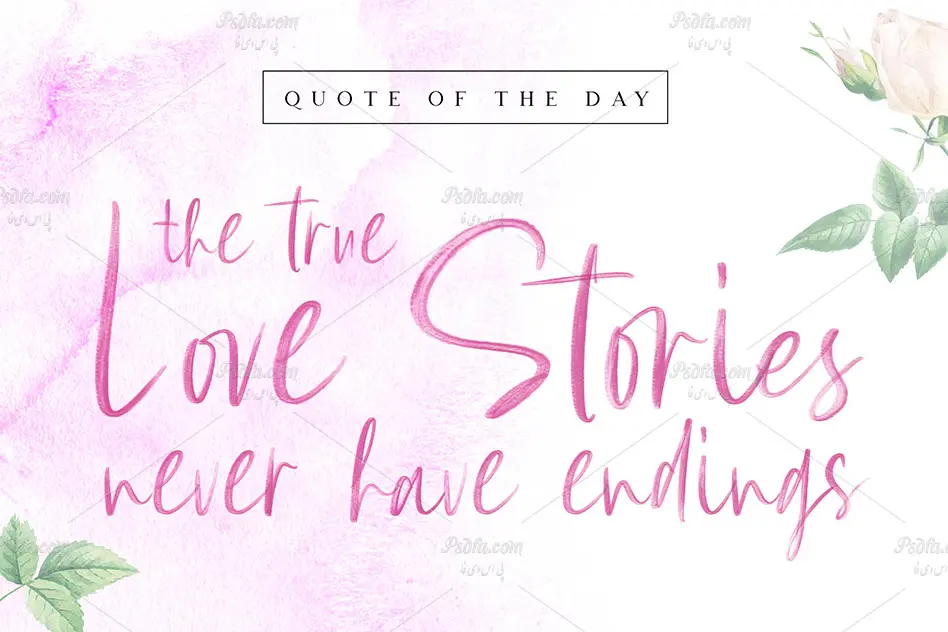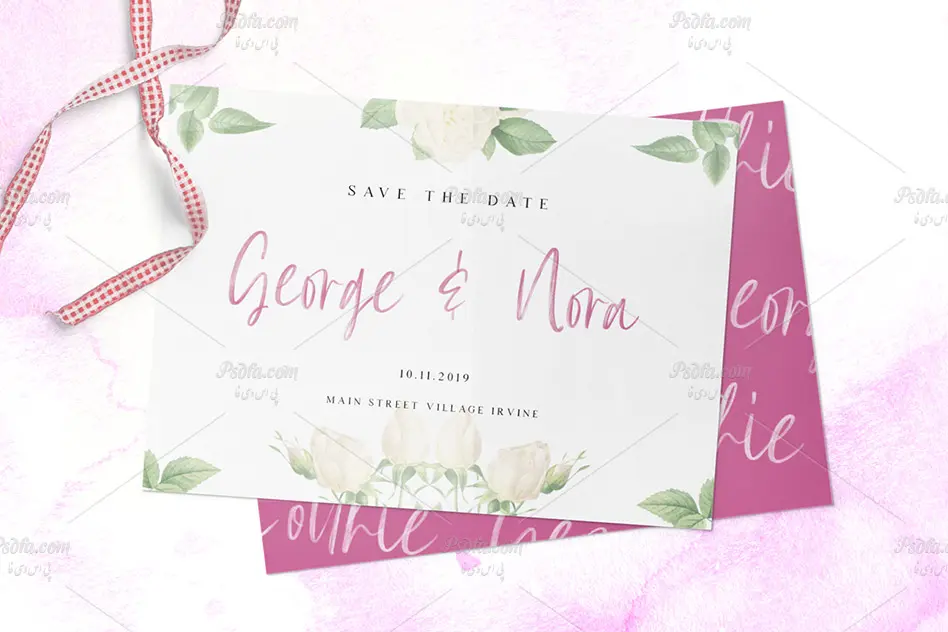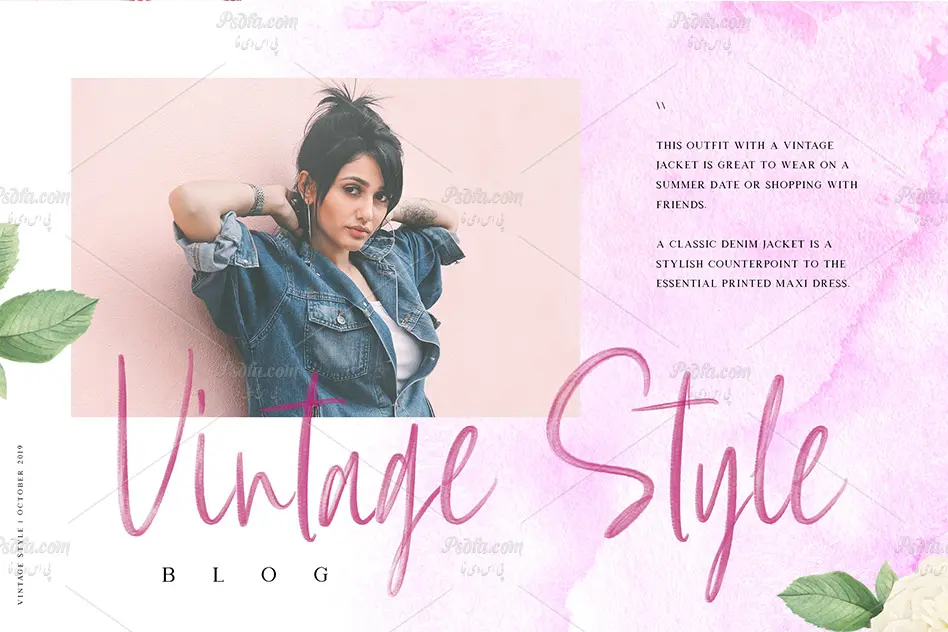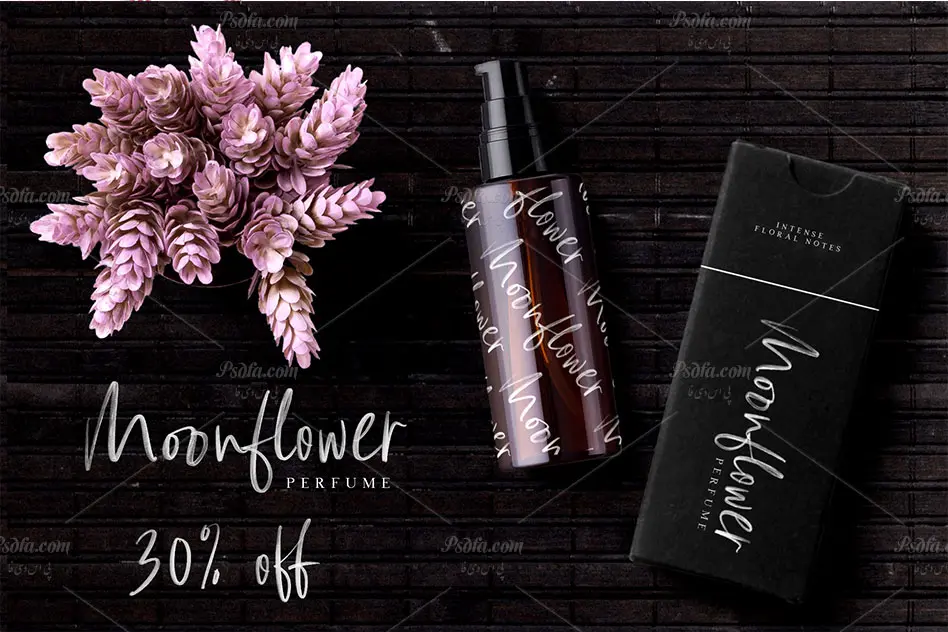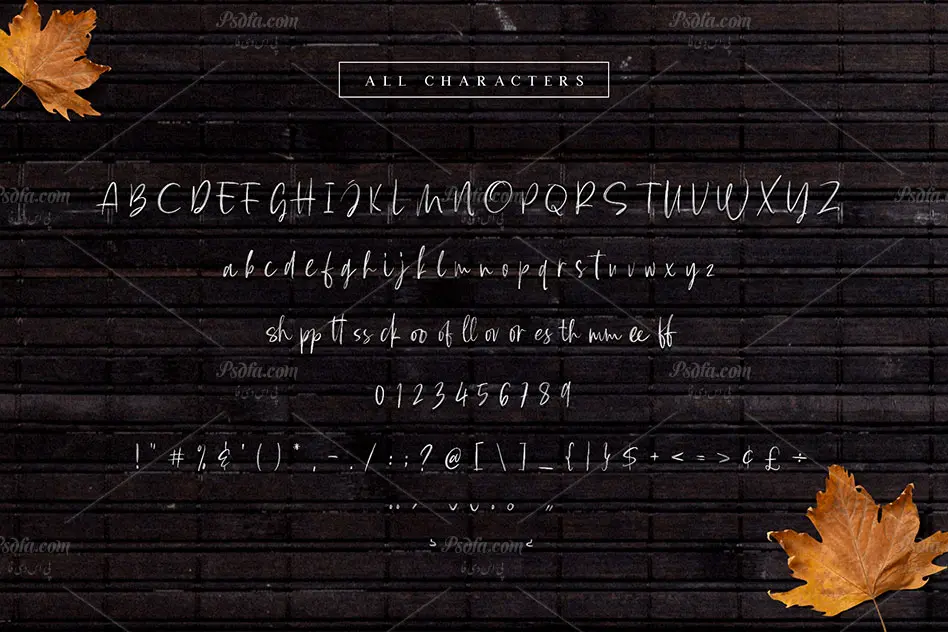
در این مطلب شاهد فونت انگلیسی دستنویس و قلمویی Rose Brush SVG Font مناسب جهت استفاده در طراحی و گرافیک می باشید. این فونت زیبا در قالب یک فایل otf بر روی سایت قرار گرفته است که با نصب این فایل در پوشه فونت های سیستم قادر به استفاده از آن در نرم افزار های گرافیکی از جمله نرم افزار محبوب فتوشاپ و … خواهید بود. فونت Rose Brush از دسته اسکریپت فونت هایی است که به صورت SVG و در وزن معمولی (Regular) طراحی شده است که می توانید از آن در طرح های گرافیکی خود به خصوص طراحی پوستر ، بنر ، تراکت ، بروشور ، کارت های عروسی ، کارت تبریک و … استفاده کنید.
- نام فونت : Rose Brush